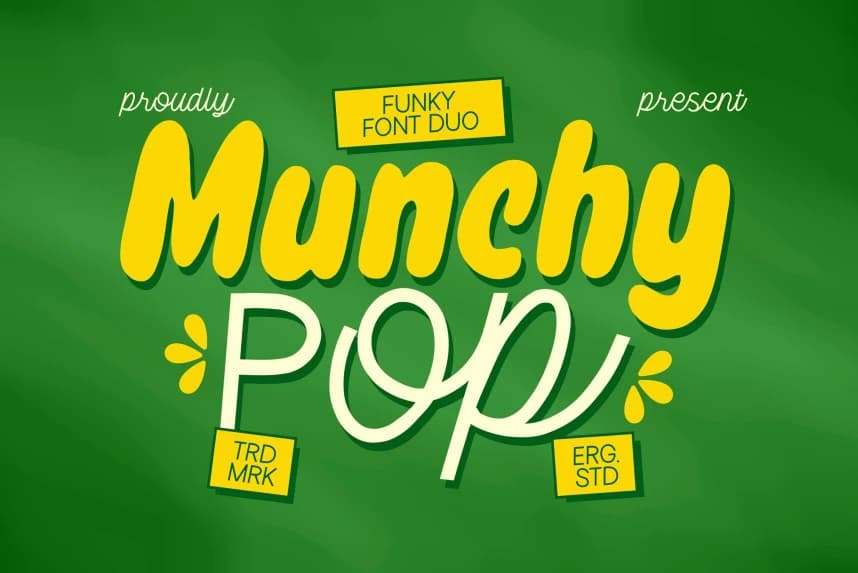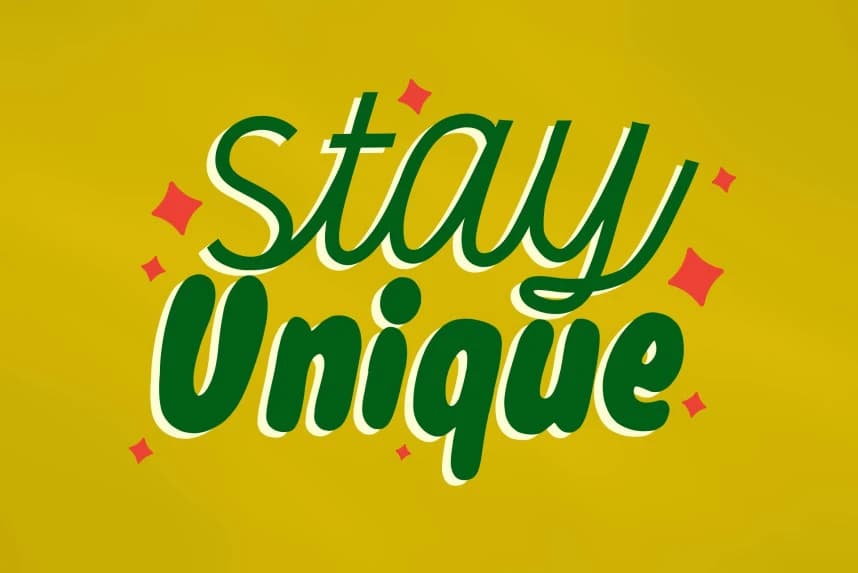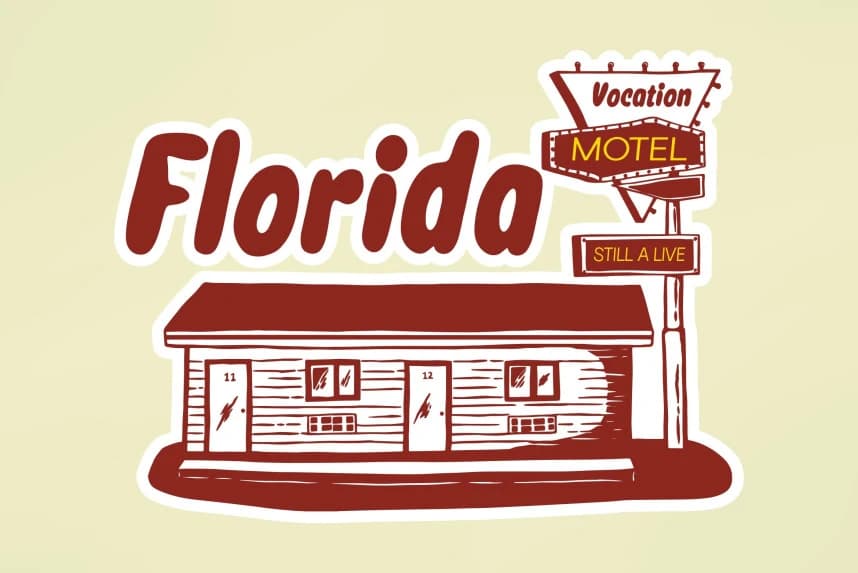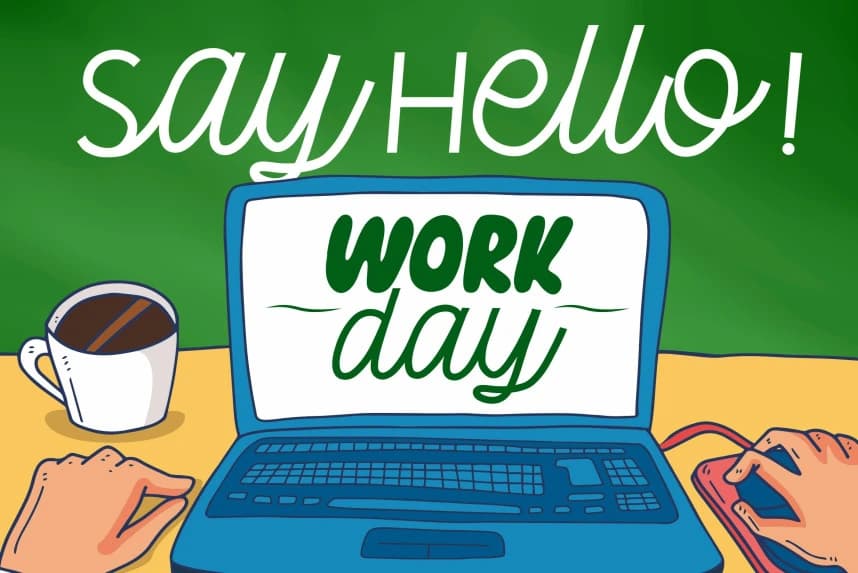
Munchy Pop Font, oyuncu ve enerjik bir font ikilisi olarak tek bir canlı paket içinde cesur kişiliği ve akıcı zarafeti bir araya getirir. Dikkat çekmek üzere tasarlanan bu ikili, kalın ve göz alıcı bir gösterim stili ile akıcı bir el yazısı stilini birleştirerek kontrast ve çekicilik katar.
Munchy Pop Font, oyunbaz ve enerjik bir font ikilisi olup cesur kişiliği ile akıcı zarafeti tek canlı paket içinde bir araya getirir. Göz alıcı olması için tasarlanan bu ikili, kalın ve dikkat çekici bir display stilini akıcı bir el yazısıyla birleştirerek kontrast ve çekicilik katar.